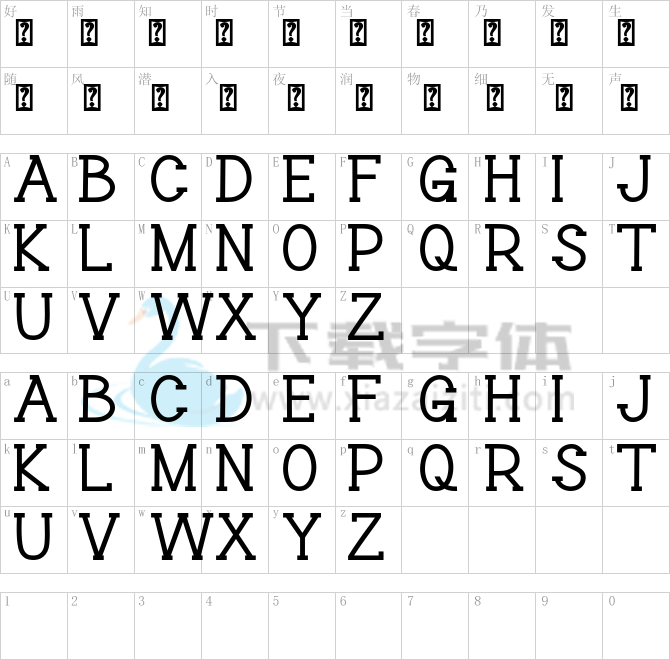
Aterline.ttf字体下载
Aterline.ttf字体下载,这款字体结构工整、笔画清晰,兼顾美观与易读性,适用于标题、正文、海报、包装、LOGO 等多种场景。字形优雅稳定,风格百搭耐看,适配日常排版与创意设计,让文字呈现更舒适、更具质感。Aterline.ttf字体下载一笔一画,皆是细节,以均衡的比例、流畅的线条打造舒适视觉体验,字形端正大气,风格简约现代。无论是商业设计、品牌宣传还是日常排版,都能轻松驾驭,让文字更有格调与力量。Aterline.ttf字体下载字体下载。